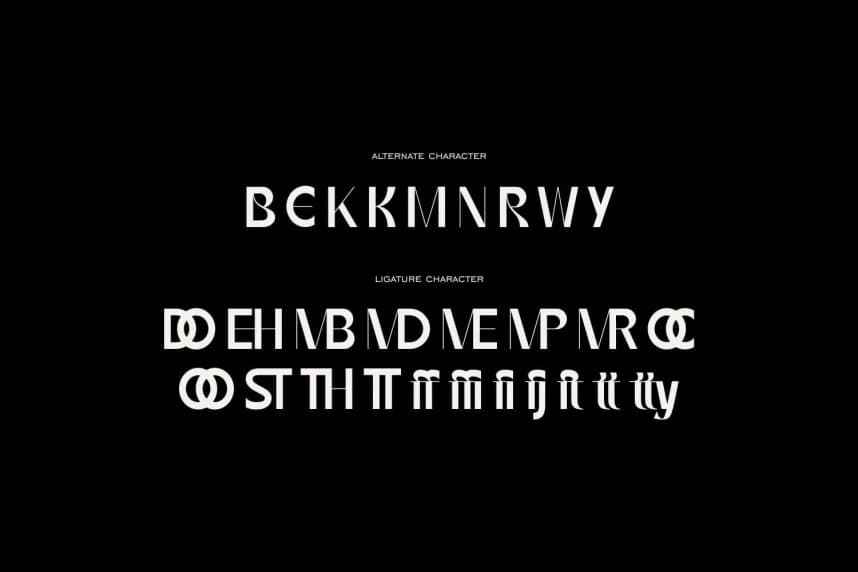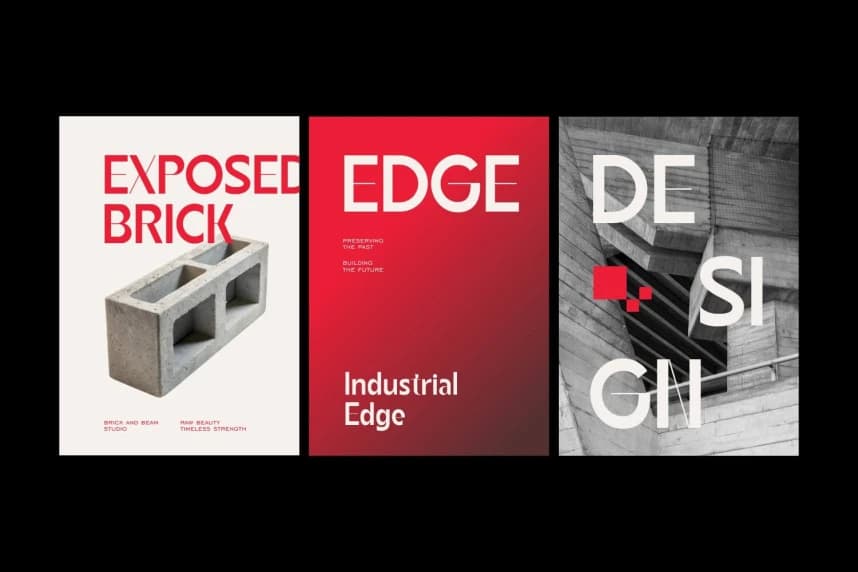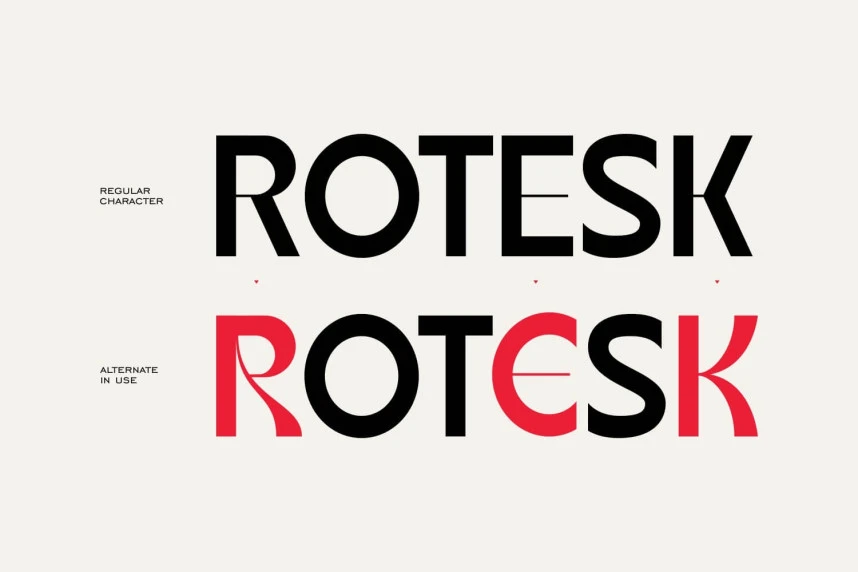
Roigant Font
Roigant Font, modern ve minimalist bir sans-serif gösterim yazı tipi olup şık geometrik biçimleri benzersiz sanatsal dokunuşlarla dengeler ve çağdaş bir zarafet izlenimi sunar; etkileyici görsel ifadeler yaratmaya uygun bir tasarımdır.
Roigant Font, modern ve minimalist bir sans-serif gösterim yazı tipidir; şık geometrik formları benzersiz sanatsal dokunuşlarla dengeleyerek çağdaş sofistikasyon izlenimi sunar ve etkileyici görsel ifadeler yaratmak için idealdir.